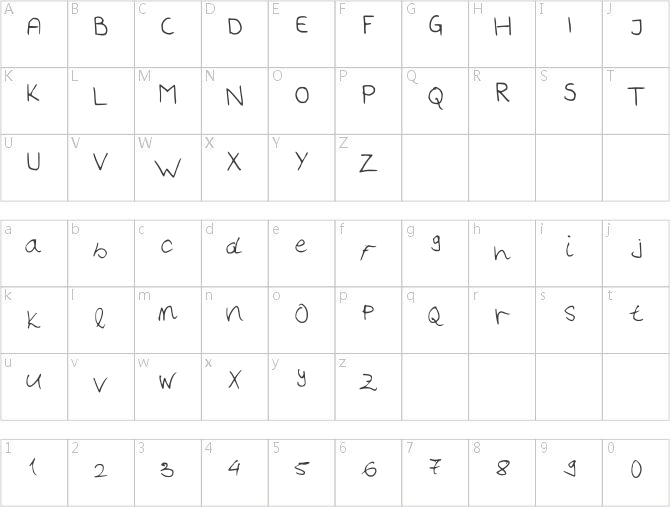
Handwriter 詳情頁(yè)
Handwriter字體字庫(kù)是一款讓人賞心悅目、百看不厭的英文字體,適合各類(lèi)廣告和產(chǎn)品包裝設(shè)計(jì)應(yīng)用,字體大小0.02MB,格式為ttf字體,上傳用戶是373790005,作者/版權(quán)方為未知